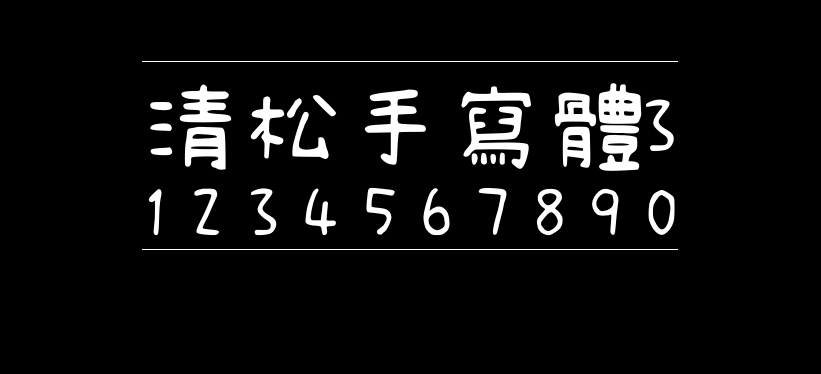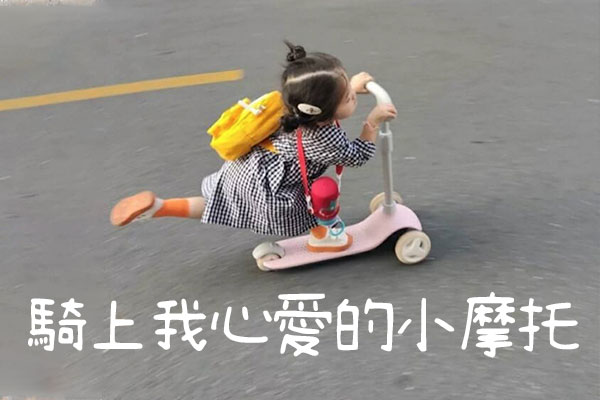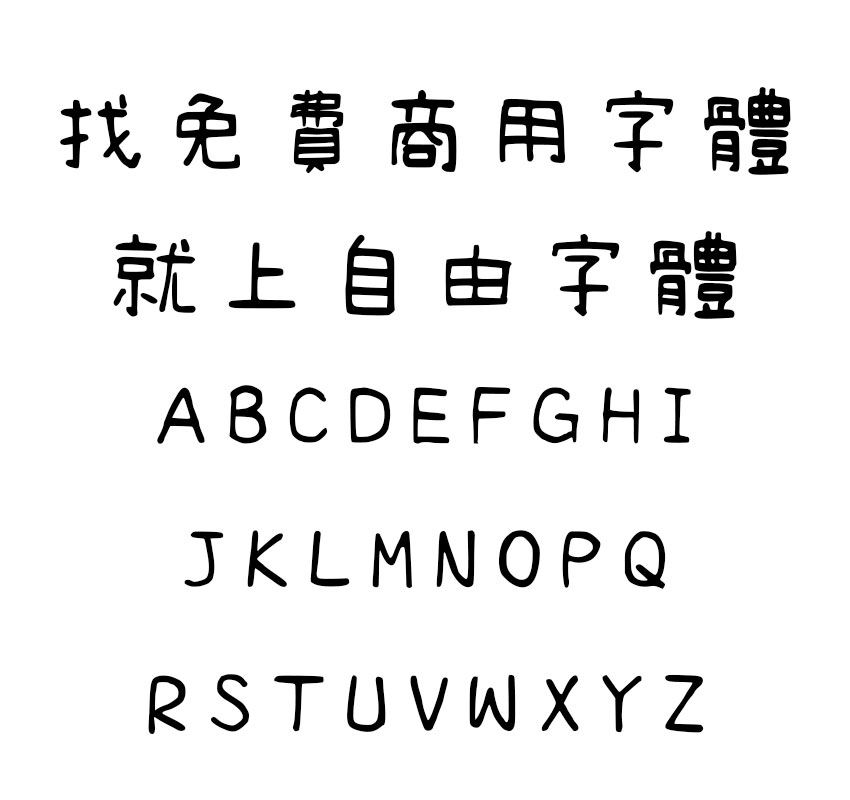
清松手写体3
清松手写体3(JasonHandwriting3 清松手寫體3)是台湾游清松在稿纸上用原子笔手写,通过“守写字”网站产生出初稿字型档,再通过字体软件制作加工而成的手写字型。
清松手写体手写字型,没有一般电脑字型的生硬感,多了几分手写般的自然感。不论是中文、英文、符号数字,适合在电脑屏幕上阅读、排版、打印出来效果也很棒!清松手写体3相较于前两款,更具备有手写的可爱风格。